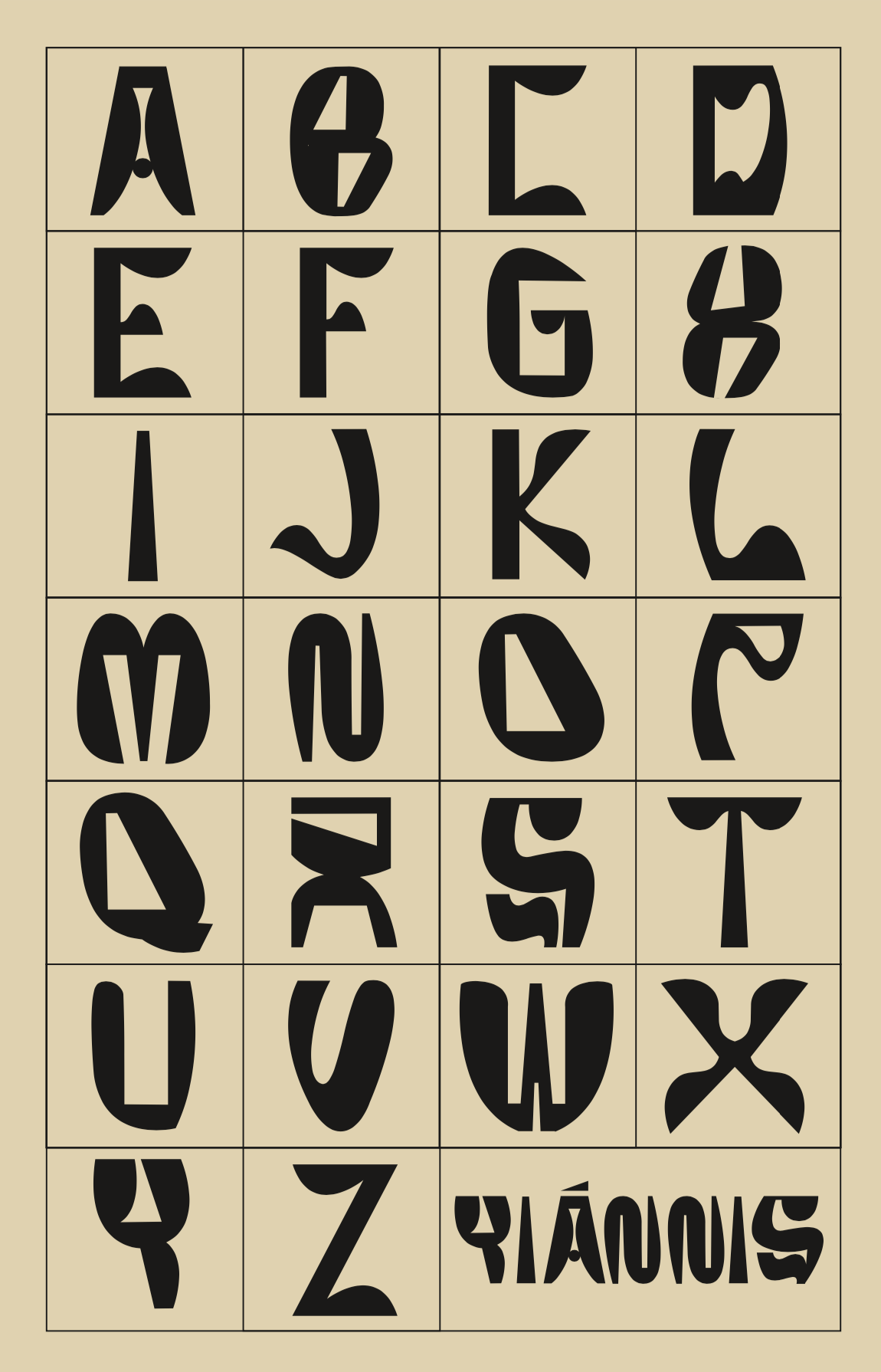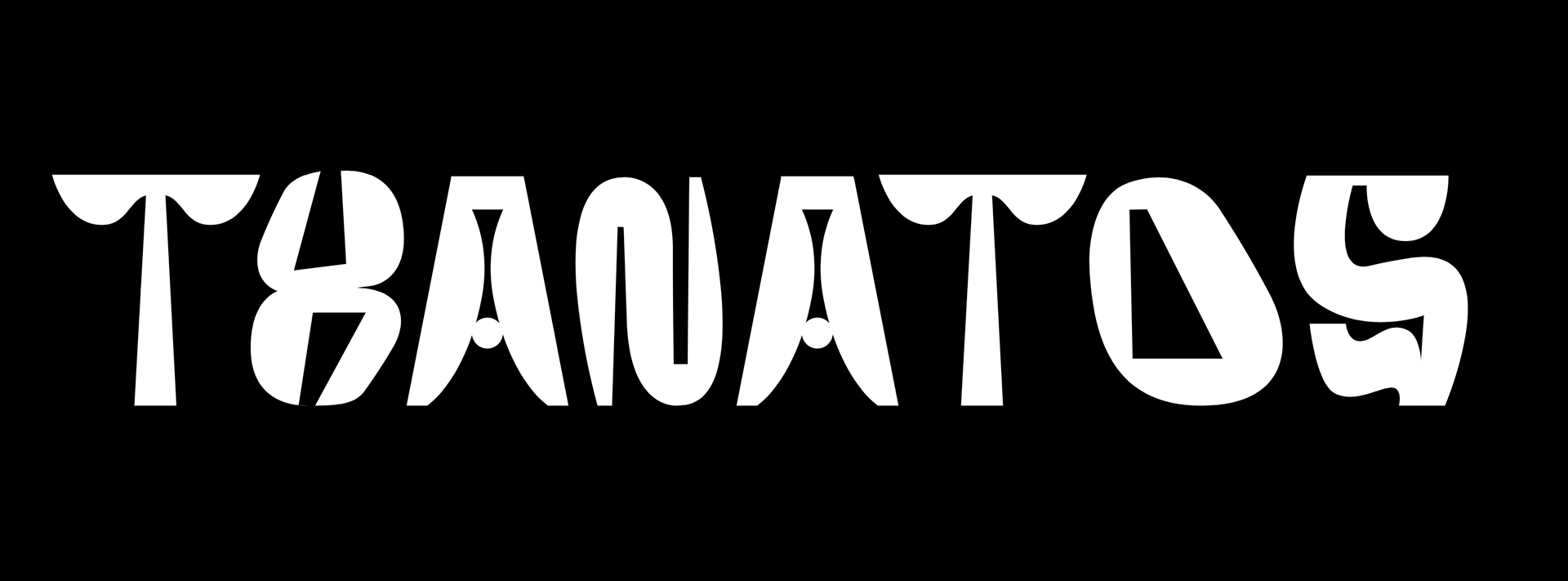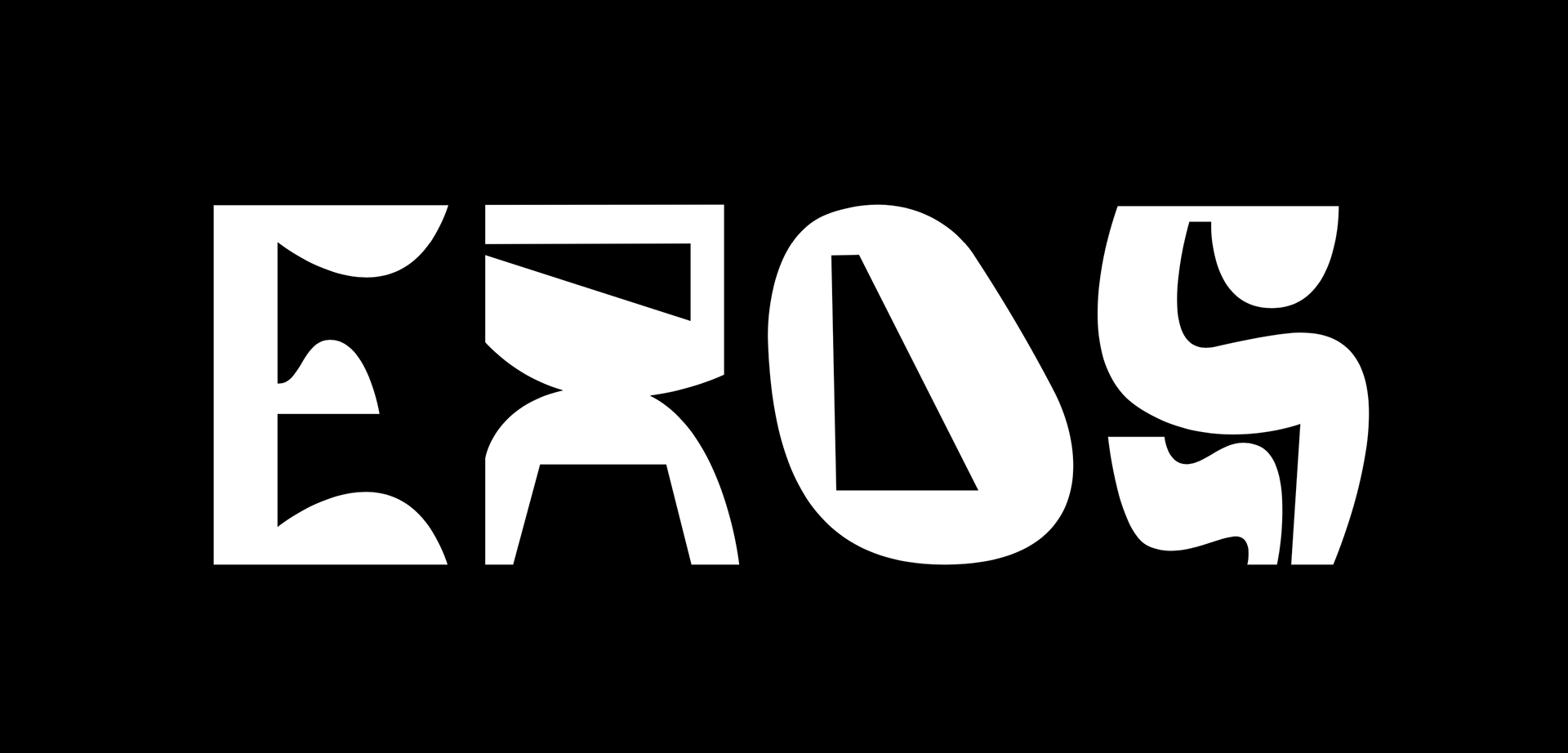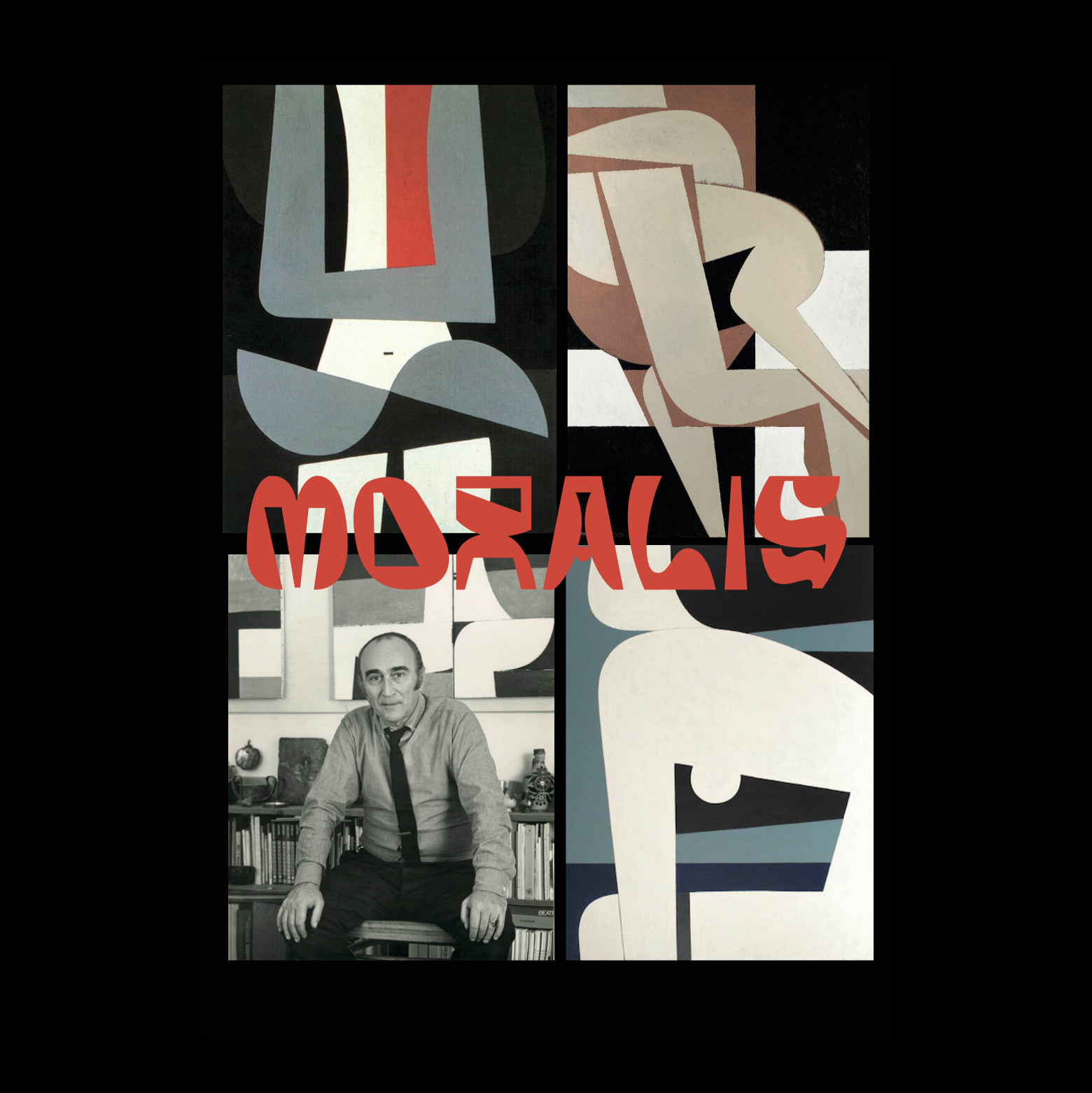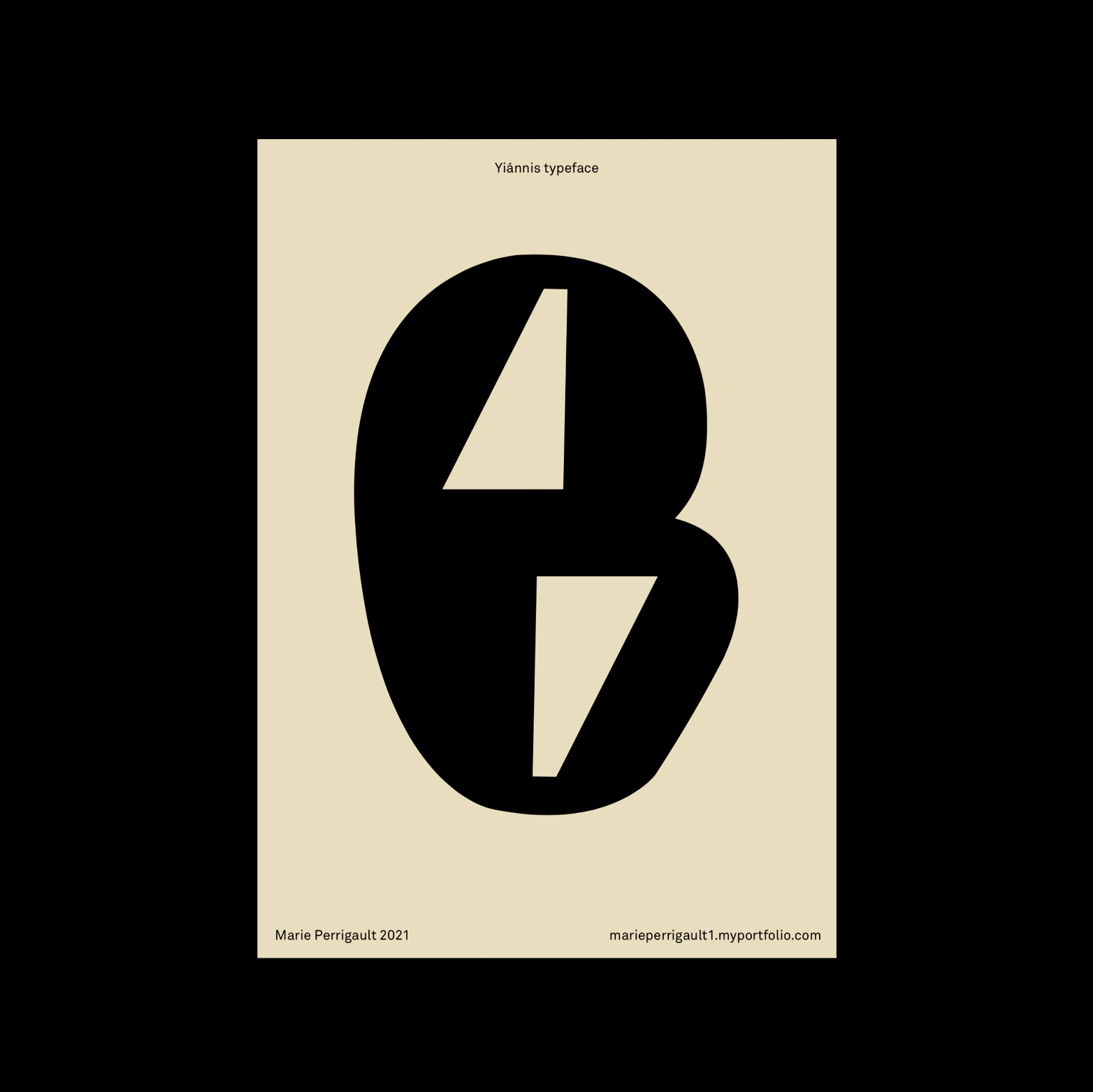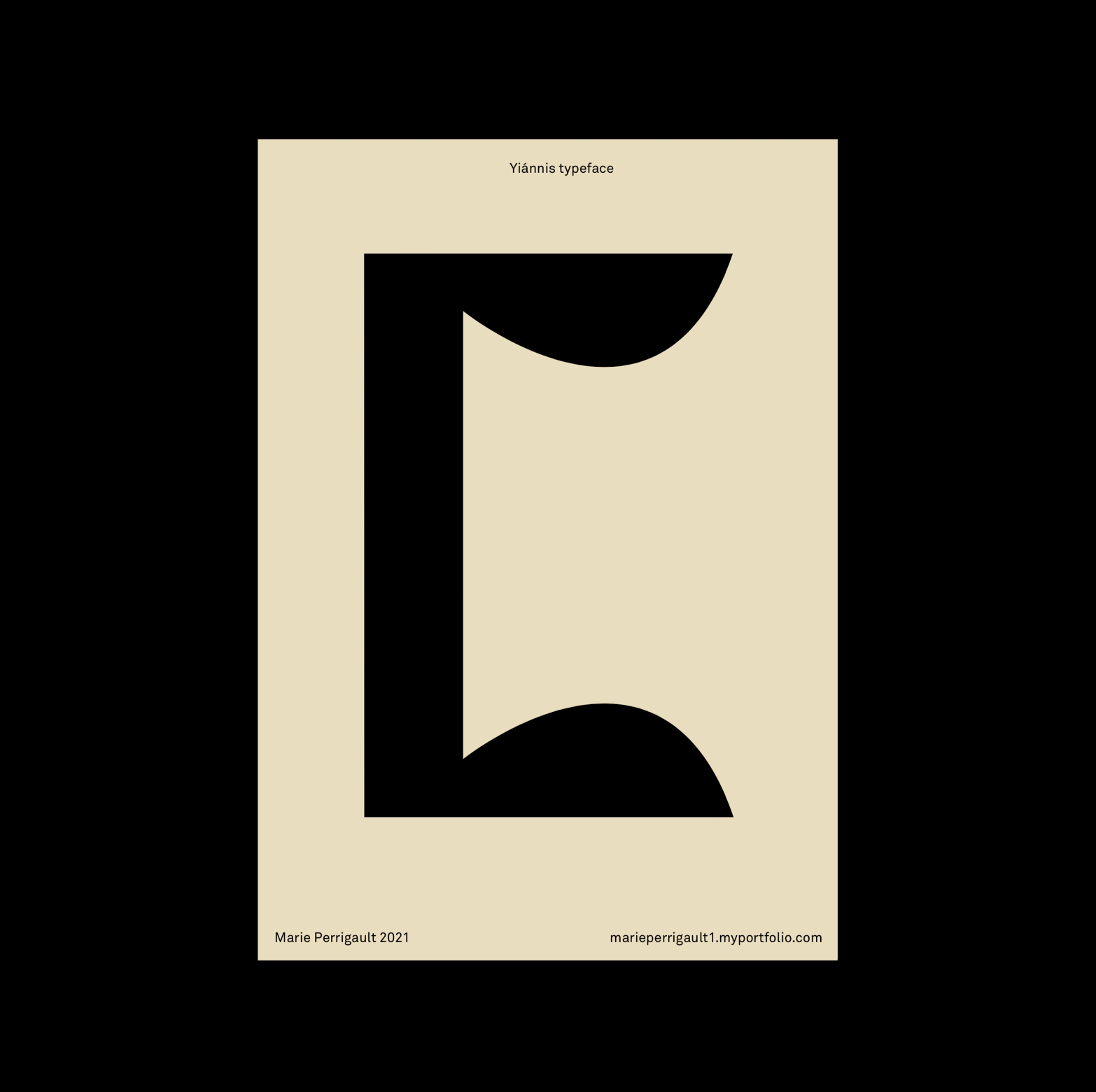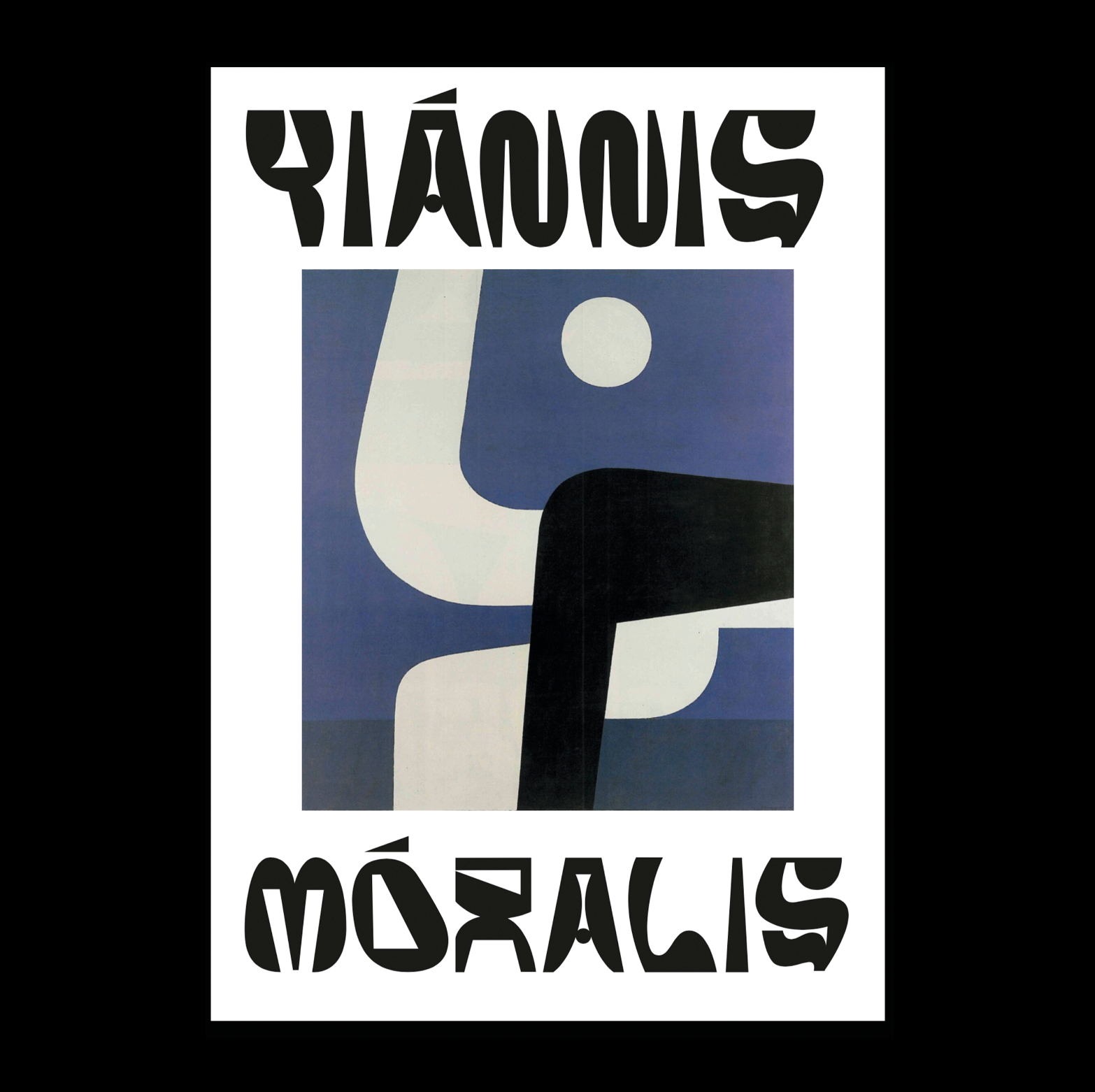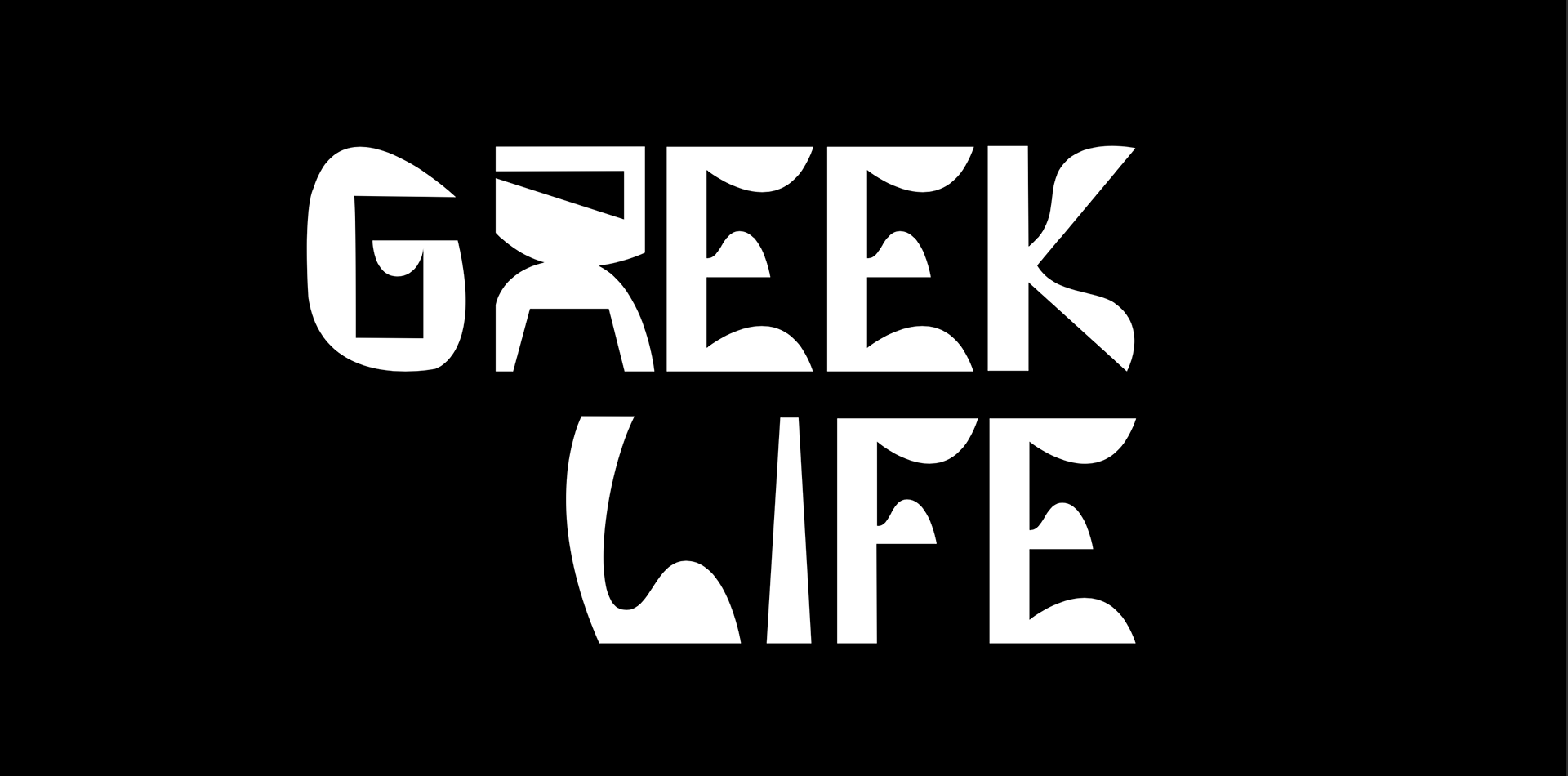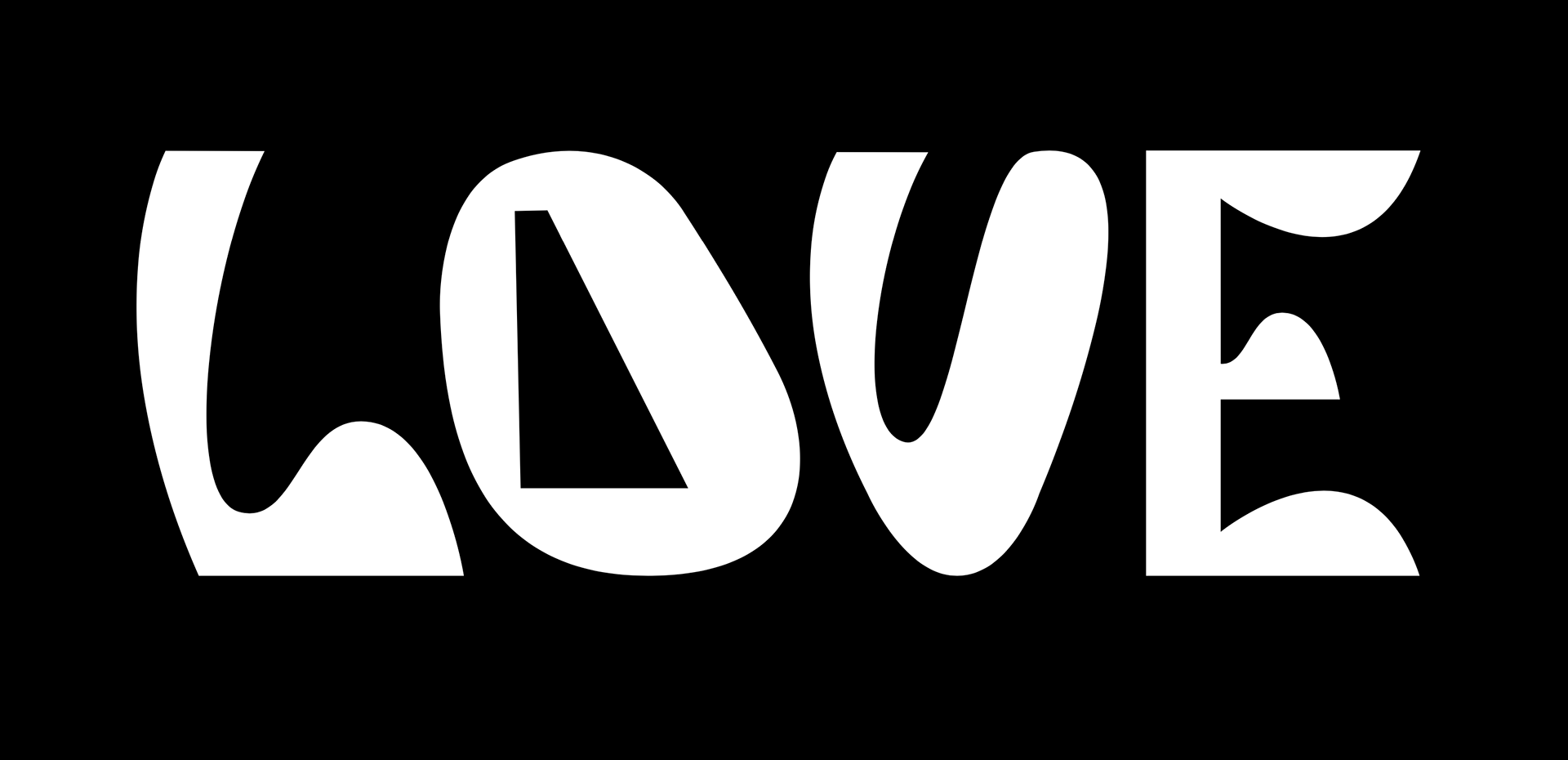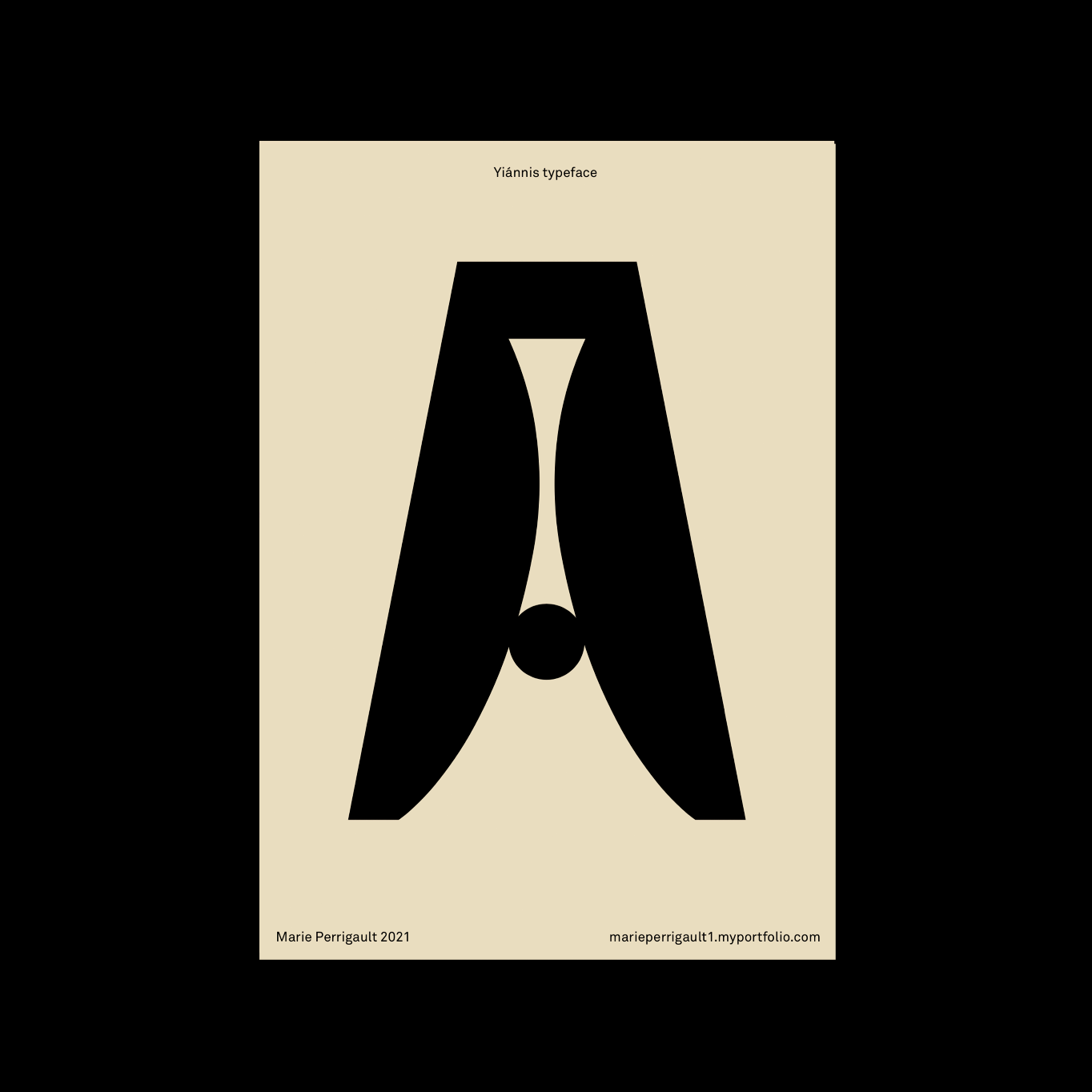
La typographie Yiannis est un dessin typographique réalisé en hommage au peintre grecque des années 30 Yiannis Moralis. Une oeuvre que j'ai découvert lors de mon travail à Athènes. Une réalisation prolifique et diversifiée qui évoque parfois l'art de Picasso. J'ai tenté de retranscrire son travail autour de la forme pour une typographie de titrage puissante et incarnée.
The Yiannis typography is a typographic design created in homage to the 1930s Greek painter Yiannis Moralis.A work I discovered while working in Athens. A prolific and diverse body of work that sometimes evokes the art of Picasso. I attempted to transcribe his work through form for a powerful and embodied typography for the title.